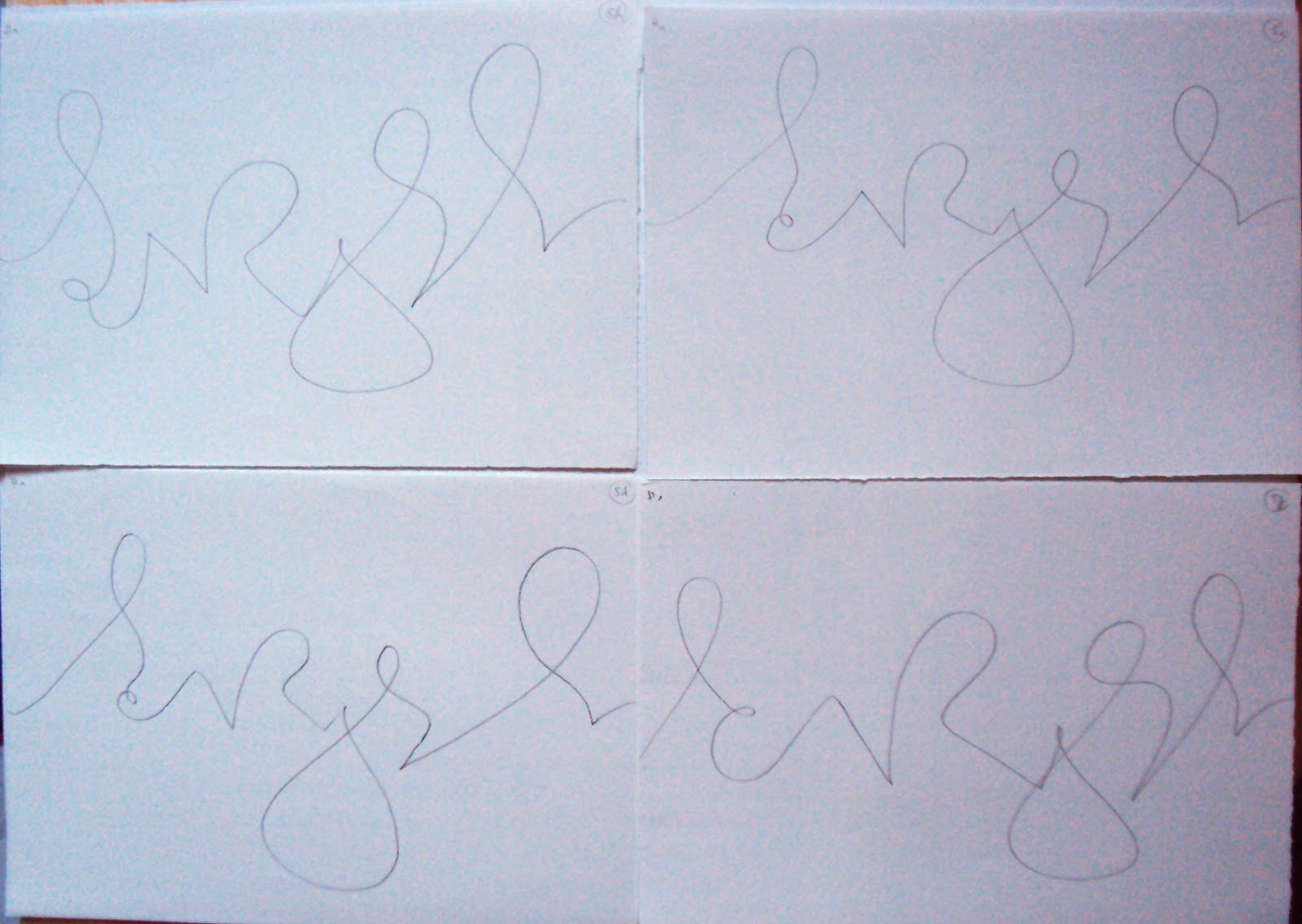
Liliane Buchi a encadré un stage autour de la Lapis Niger : la plus ancienne inscription romaine connue (datant environ du VIe siècle av. J.C.).
On a, tout d'abord, recopié ces inscriptions à la plume palette pour les apprivoiser !
>> voir différentes feuilles intégrées dans le livret
On les a étudiées afin d'en extraire toutes les lettres de l'alphabet...
A partir de cet alphabet, nous avons pu écrire des mots, voire des textes...
En parallèle de ce travail d'écriture, nous avons travaillé avec des encres lino sur différents supports en suivant les différentes consignes données par Liliane.
Cela donne un nombre important de feuilles...
La plupart ont été conservées et ont été assemblées sous forme de livret !
Voici ce que cela donne ! Il n'est, pour l'instant, pas terminé...
Point à la ligne avec Edwige Timmerman
Voyage vers la gestuelle...
Edwige propose une démarche inédite à partir des fondements du trait d'écriture : la ligne et le point ou inversement !
Différents exercices à faire, tout d'abord, au crayon puis avec divers outils scripteurs... dans un sens, puis dans un autre...
en regardant, sans regarder... lentement ou rapidement...
Les utiliser pour écrire les mots suggérés par Edwige : arabesque et interligne.
Tester le tracé continu... avec différents outils scripteurs !
Tout cela pour libérer nos tracés... sur format A5 > de nombreuses variations, "essais" !
Puis sur formats A3 > gestion d'un espace plus grand à partir des mêmes tracés (avec 3 outils scripteurs différents : variations en épaisseur, en texture, en contraste) à combiner pour créer une composition...
version à plusieurs mains... 3 stagiaires/3 tracés/3 outils |
Transposition de nos tracés sur le principe de la portée musicale...
Reprendre les bases de la chancelière, lettre après lettre...
Puis voir si on peut tracer ces lettres en "enlevant" des points ou des lignes...
Un petit texte avec 2 gestuelles personnelles...
à la pipette (Liliane Buchi) |
au tire-ligne |